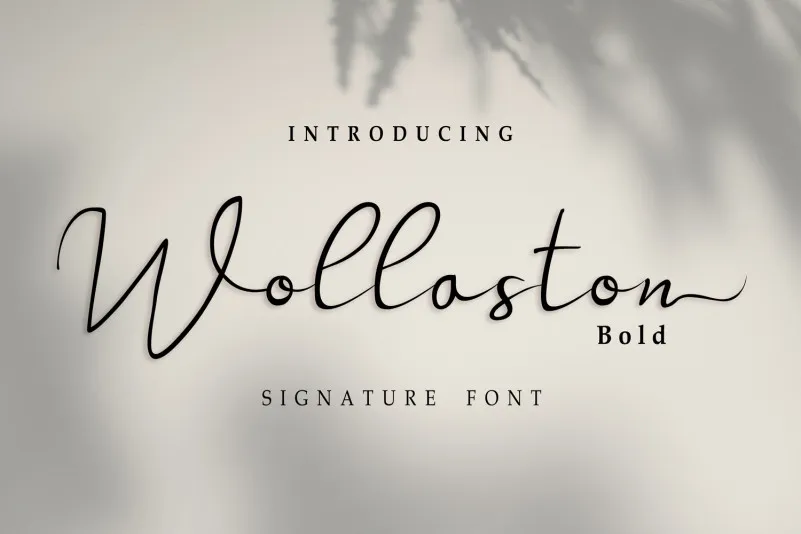
Wollaston Font – Fonte Grátis
Wollaston Font
Esta fonte foi projetada pela Rezastudio com um design clean, moderno e relaxado. Ela é ideal para adicionar ao seu design, seja ele uma assinatura ou qualquer outro elemento visual. Com um estilo agradável e semuosidade perfeita, Wollaston promete dar um toque único à sua criação. A fonte tem a característica PUA, que significa você pode acessar facilmente todos os símbolos e swashes que ela contém. Este é um recurso excelente para designers atentos ao detalhe que procuram uma fonte moderna com uma leveza e sofisticação perfeitas. Wollaston certamente faz a diferença em qualquer projeto de design, tornando-a uma opção imprescindível no seu arsenal de recursos gráficos.